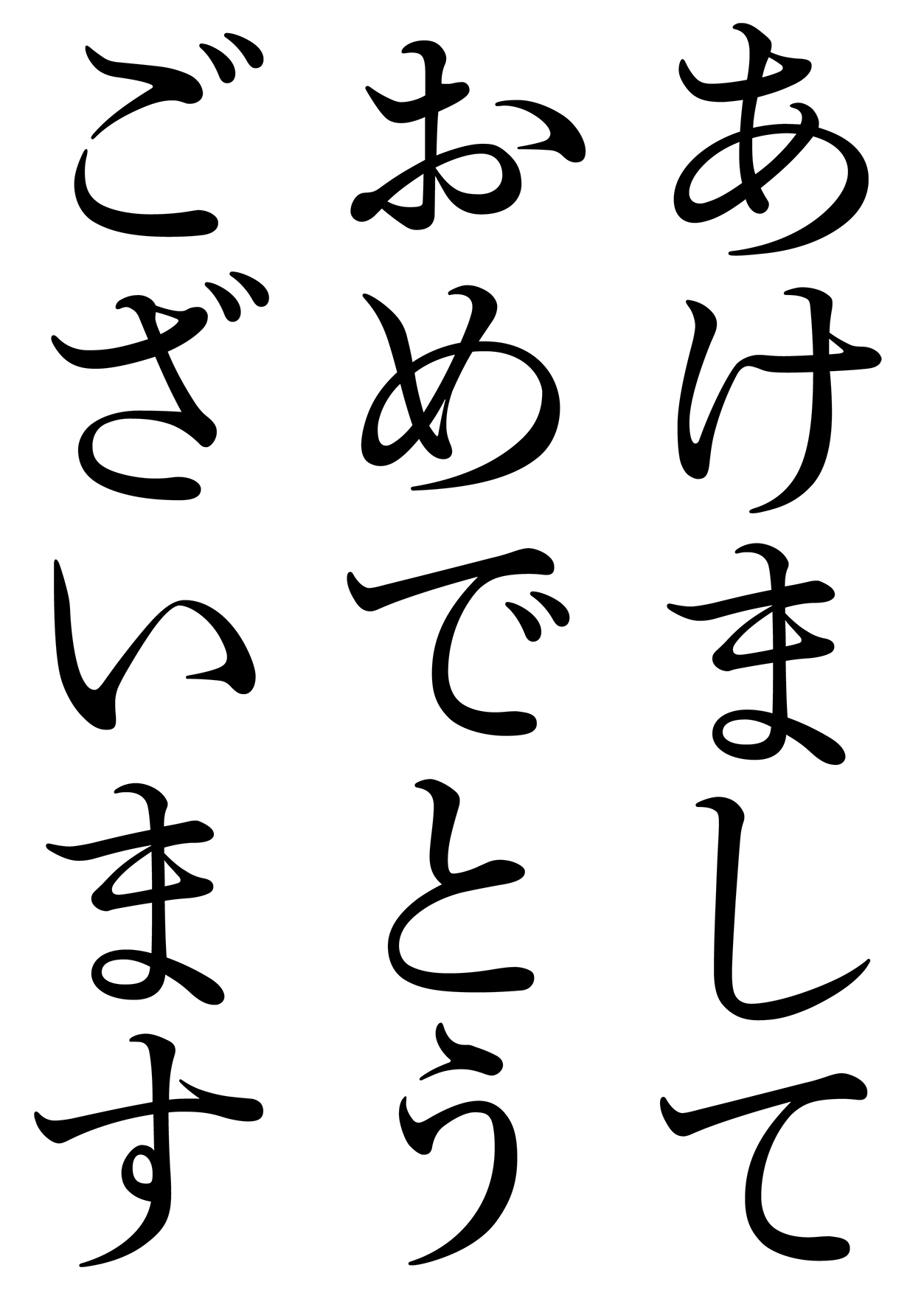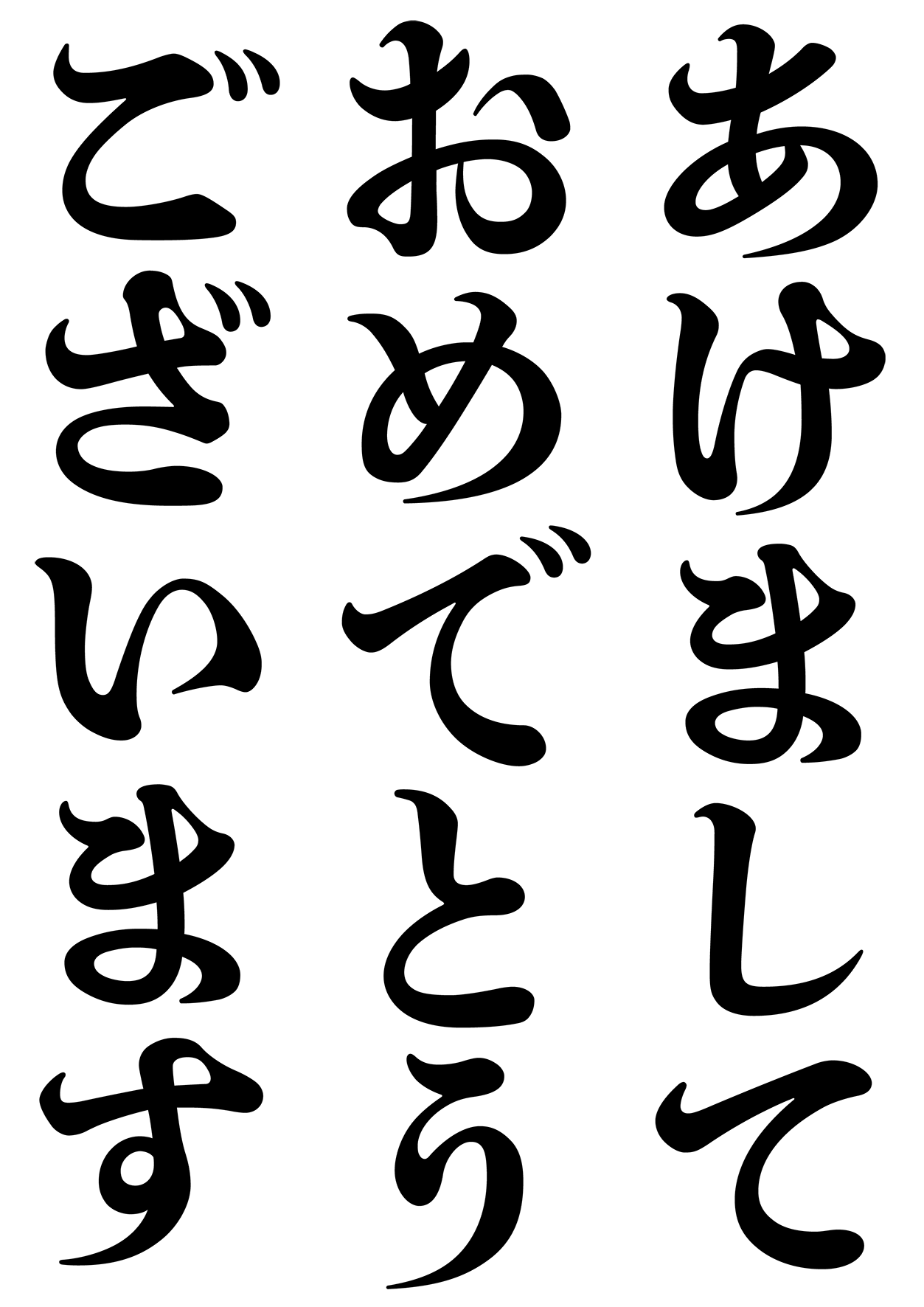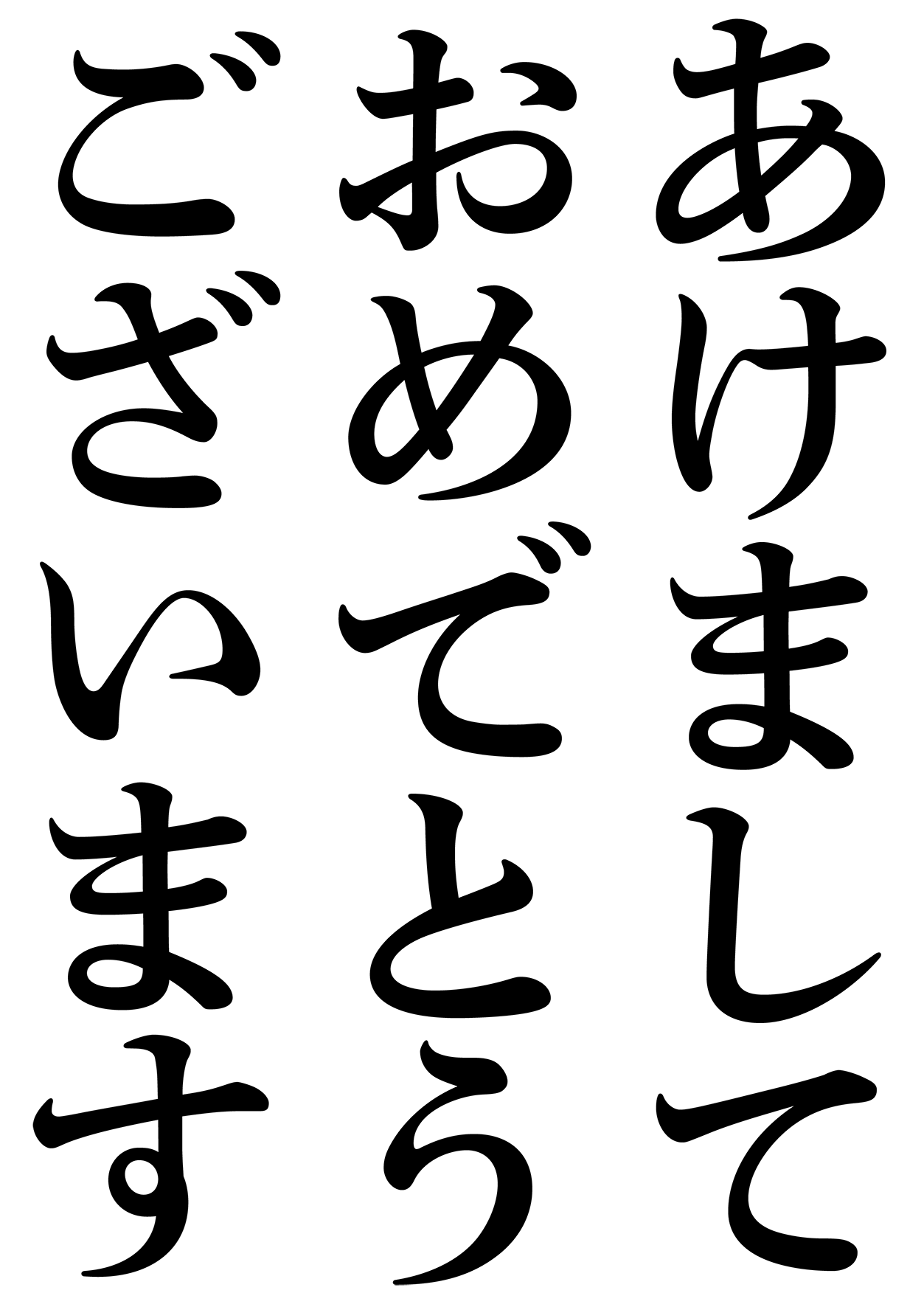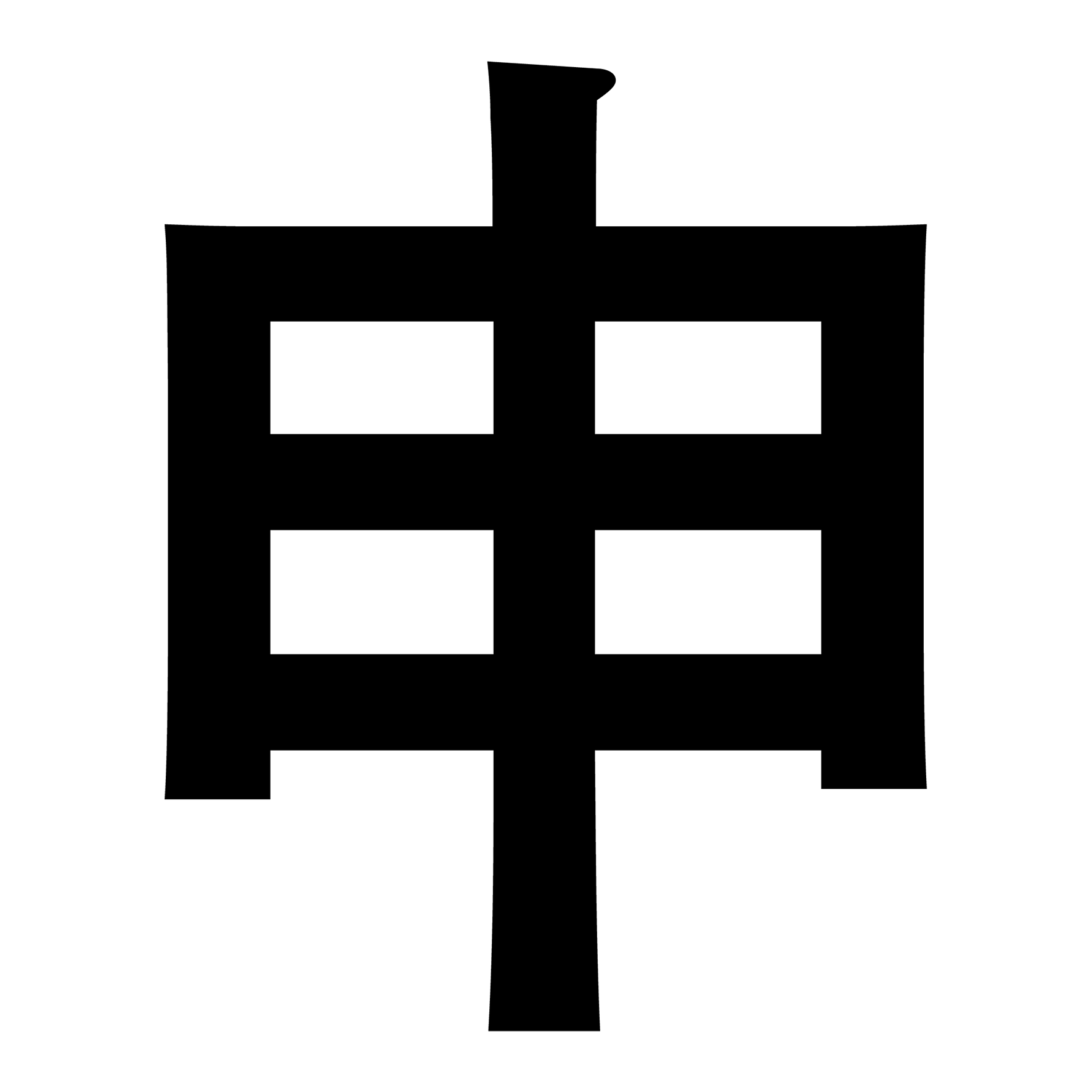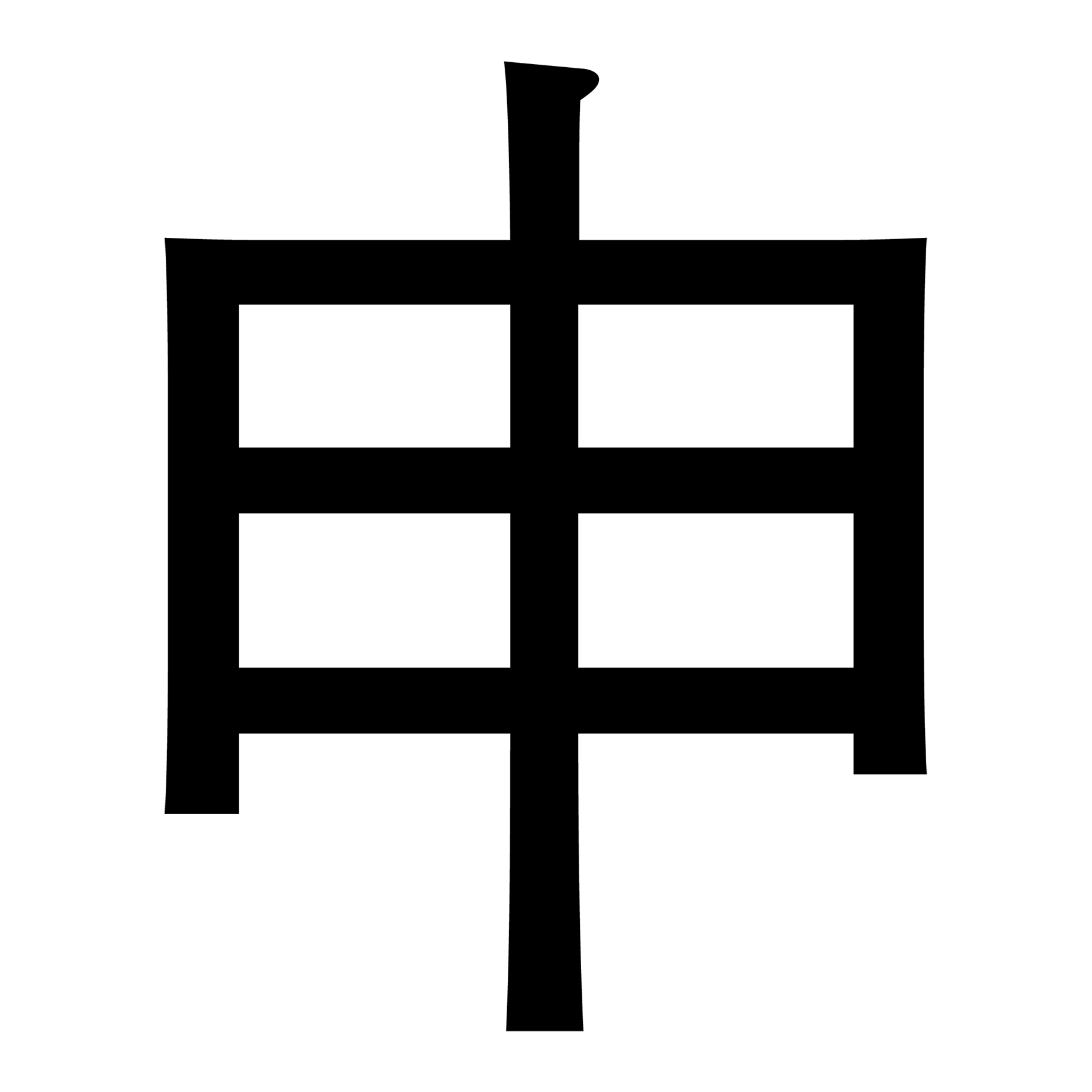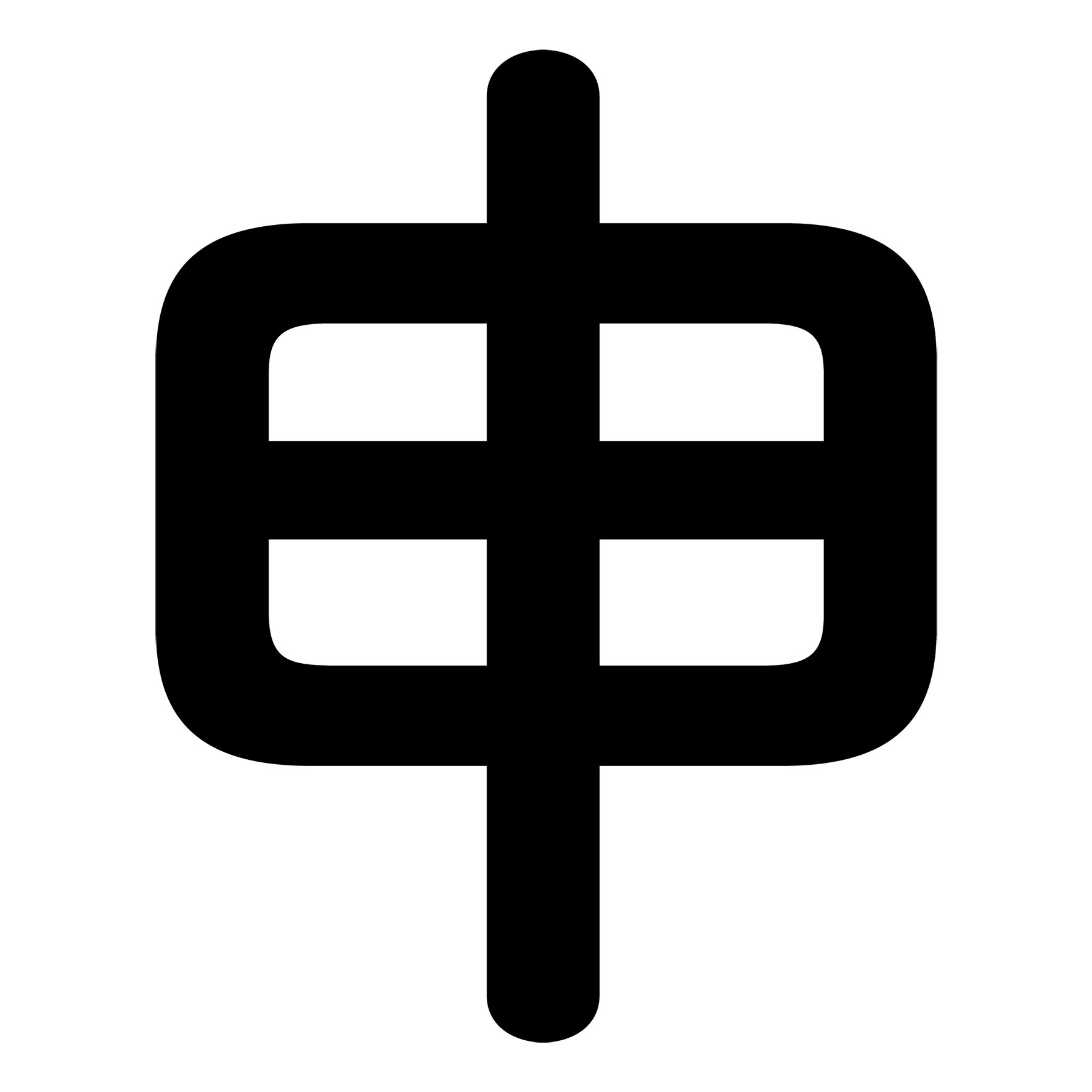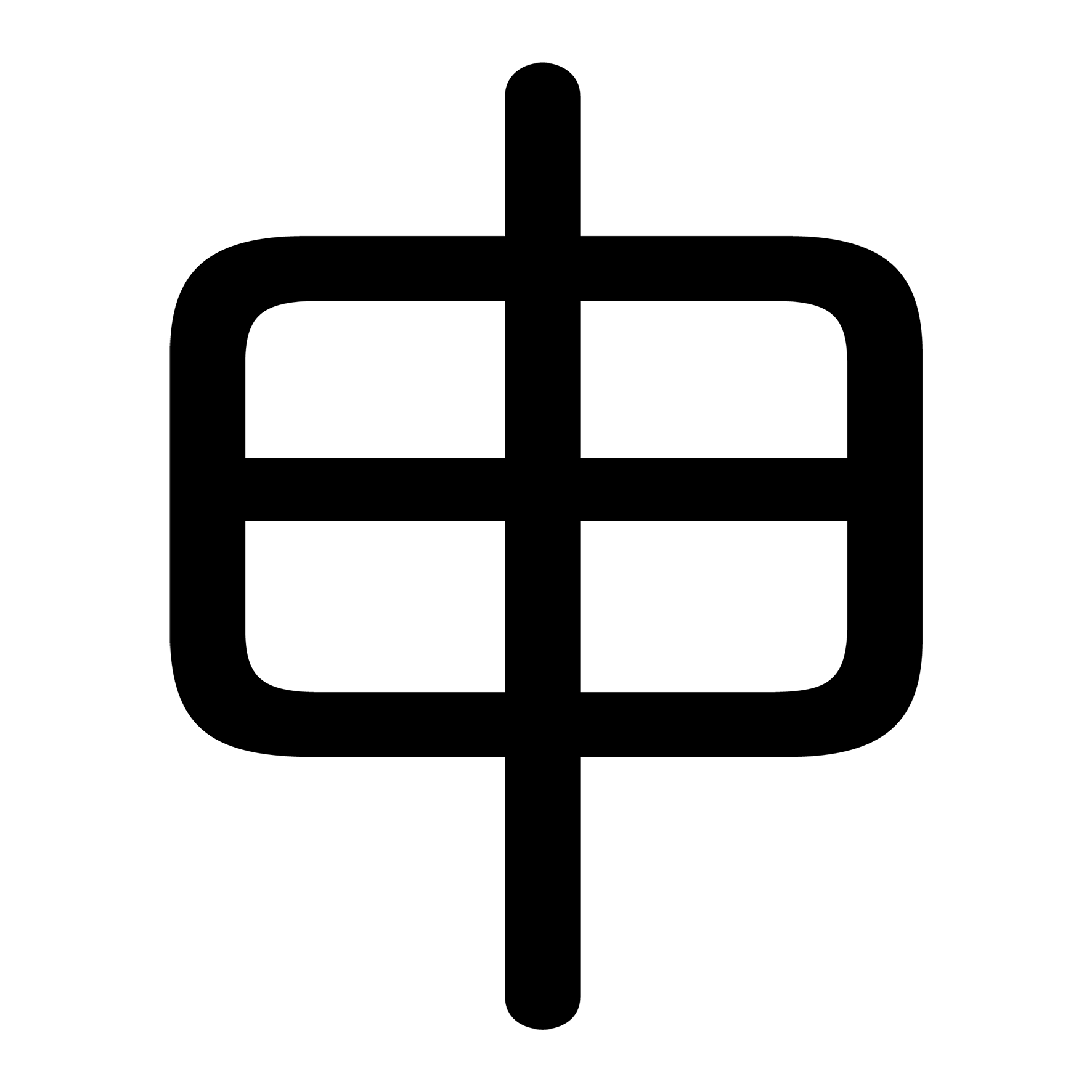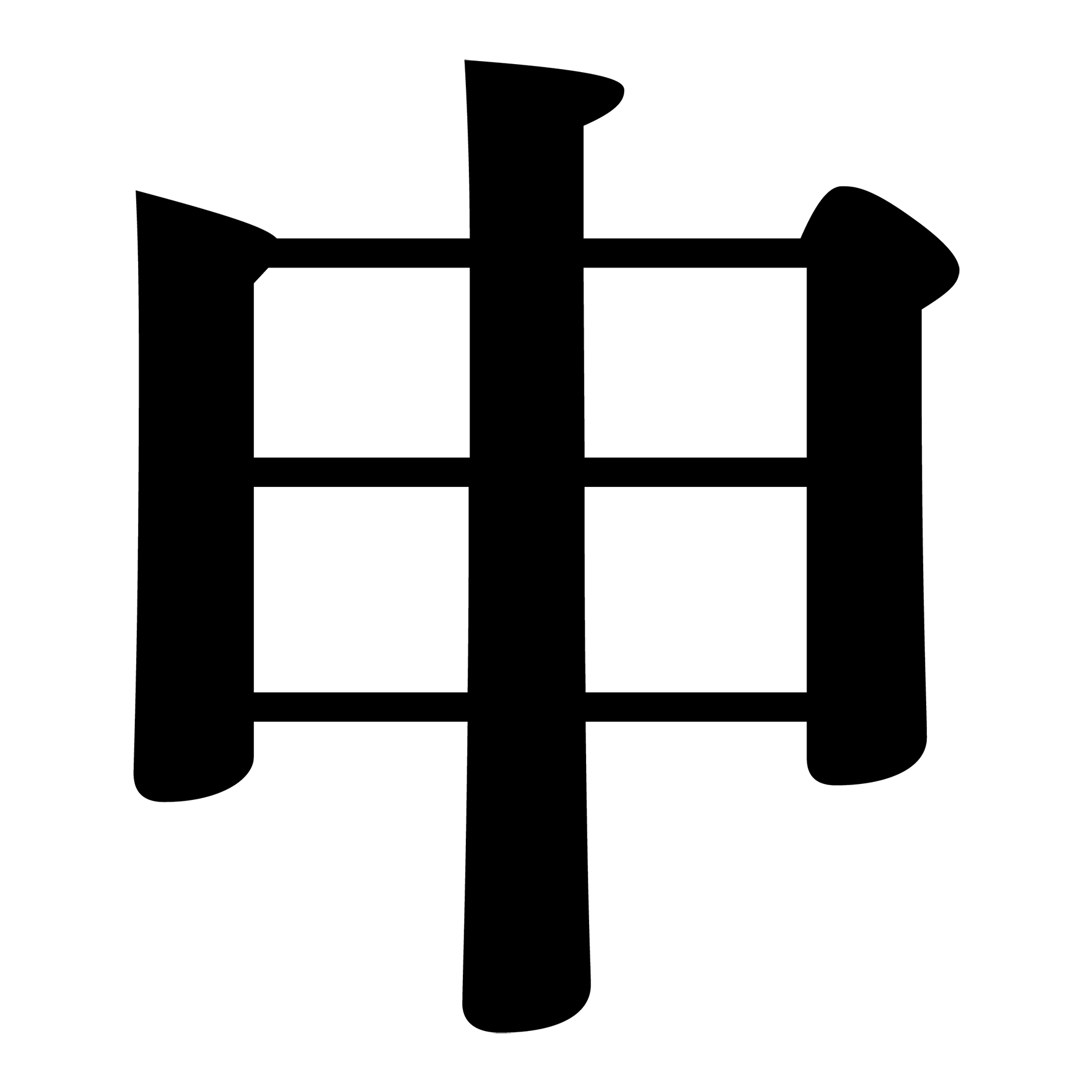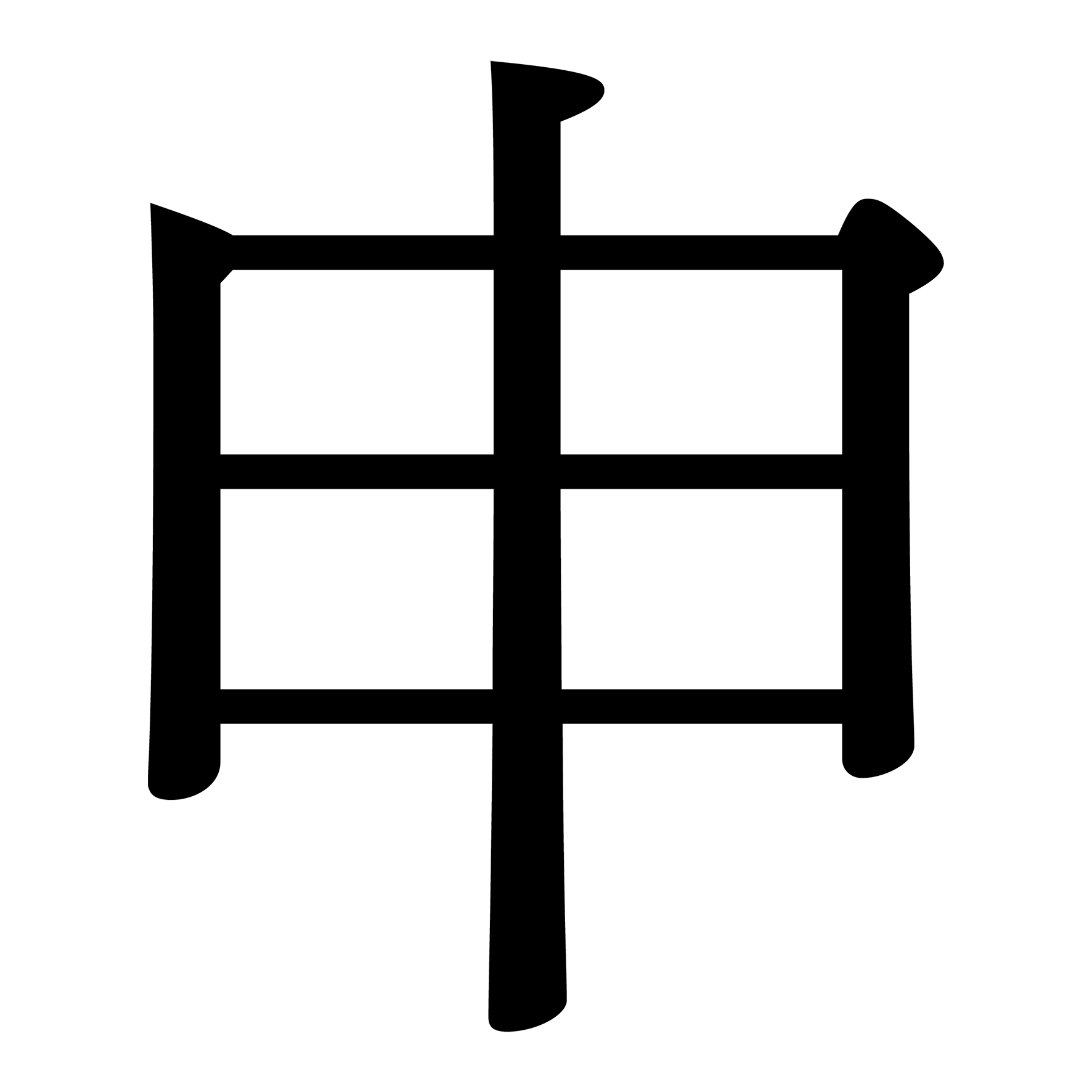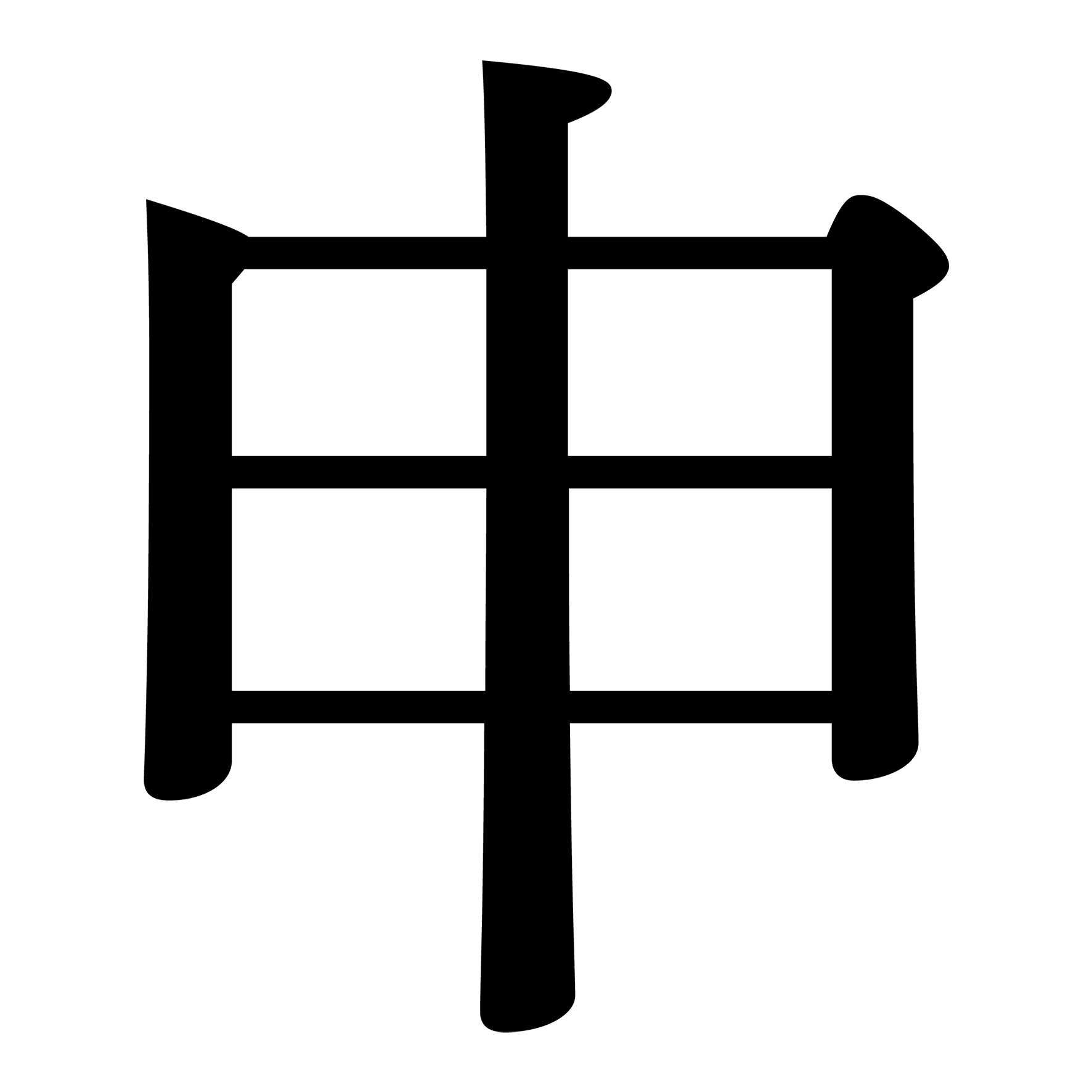
忙しい合間の息抜きに、秀英体で年賀状はいかがでしょうか。
今回のコネタは、実に5年ぶりの「秀英体で年賀状」をお届けいたします。
新年のご挨拶を新書体「秀英四号かな」、「秀英四号太かな」、「秀英アンチック」で、イラストは秀英舎・大日本印刷が誇る最大規模の見本帳、大正3年版『活版見本帖 Type Specimens』から、来年の干支である申をピックアップしてご用意いたしました。ぜひご利用ください。
まずは定番中の定番「あけましておめでとうございます」。2種類の組み方でお届けします。
いずれも、昭和初期から中期の金属活字の仮名を復刻した書体です。現在の秀英明朝のルーツ「秀英四号かな」、見出しや児童書に用いられた「秀英四号太かな」、辞書の見出しやコミックのふきだしに用いられた「秀英アンチック」。
現在の明朝体より筆の雰囲気を残し、年賀状にも適しています。
「秀英四号かな」、「秀英四号太かな」、「秀英アンチック」は仮名書体です。漢字はそれぞれ他の秀英体と組合わせて利用いただくことを想定しています。漢字仮名交じりだとこのようになります。
漢字と組合わせると、また雰囲気が変わりますね。アンチックと角ゴシックは、一転して、ポップな印象です。
猿は山の賢者、山神の使いとして信じられており、信仰の対象としても馴染みの深い動物です。 「申」は「呻(うめく)」の意味で、果実が成熟し、固まっていく状態を表しているとされます。
まずは干支の「申」の字を秀英体ファミリーで!!
賀正と書かれた袋を差し出しているジェントルマンな猿…お年玉でしょうか。
猿といえば!桃太郎のお供です。
お供の猿だけバージョンもございます。
こちらは、さるかに合戦です。(カニが怖い・・・)
猿だけバージョンも、もちろんあります。
最後におまけで、2008年にもご用意した「秀英初号明朝」の賀詞です。今回は、よく使うものをピックアップして、背景を透過にしました。
開発中の「秀英角ゴシック金M」、「秀英角ゴシック銀M」、「秀英四号かな」、「秀英四号太かな」、「秀英アンチック」も、皆様のお手元で使っていただける日が楽しみです。